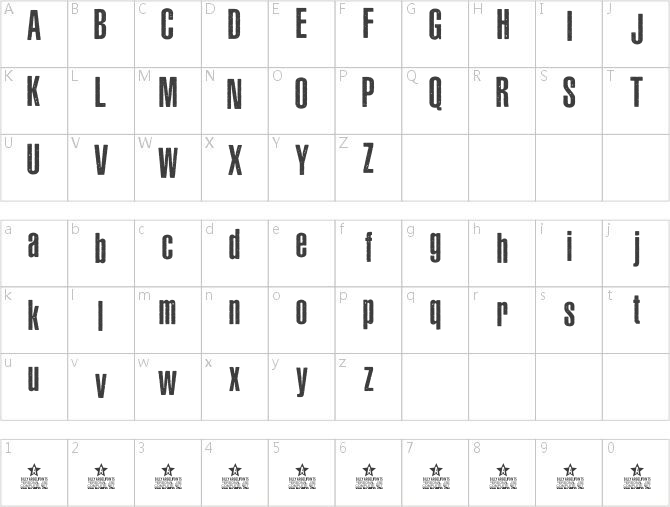
ASPHALTIC GRAIN CONDENSED PERSON 詳情頁(yè)
ASPHALTIC GRAIN CONDENSED PERSON字體字庫(kù)是一款讓人賞心悅目、百看不厭的英文字體,適合各類廣告和產(chǎn)品包裝設(shè)計(jì)應(yīng)用,字體大小1.24MB,格式為ttf字體,上傳用戶是W^xzj,作者/版權(quán)方為未知